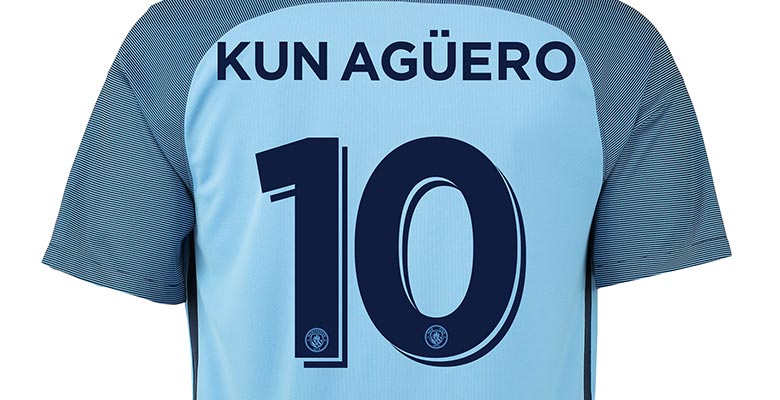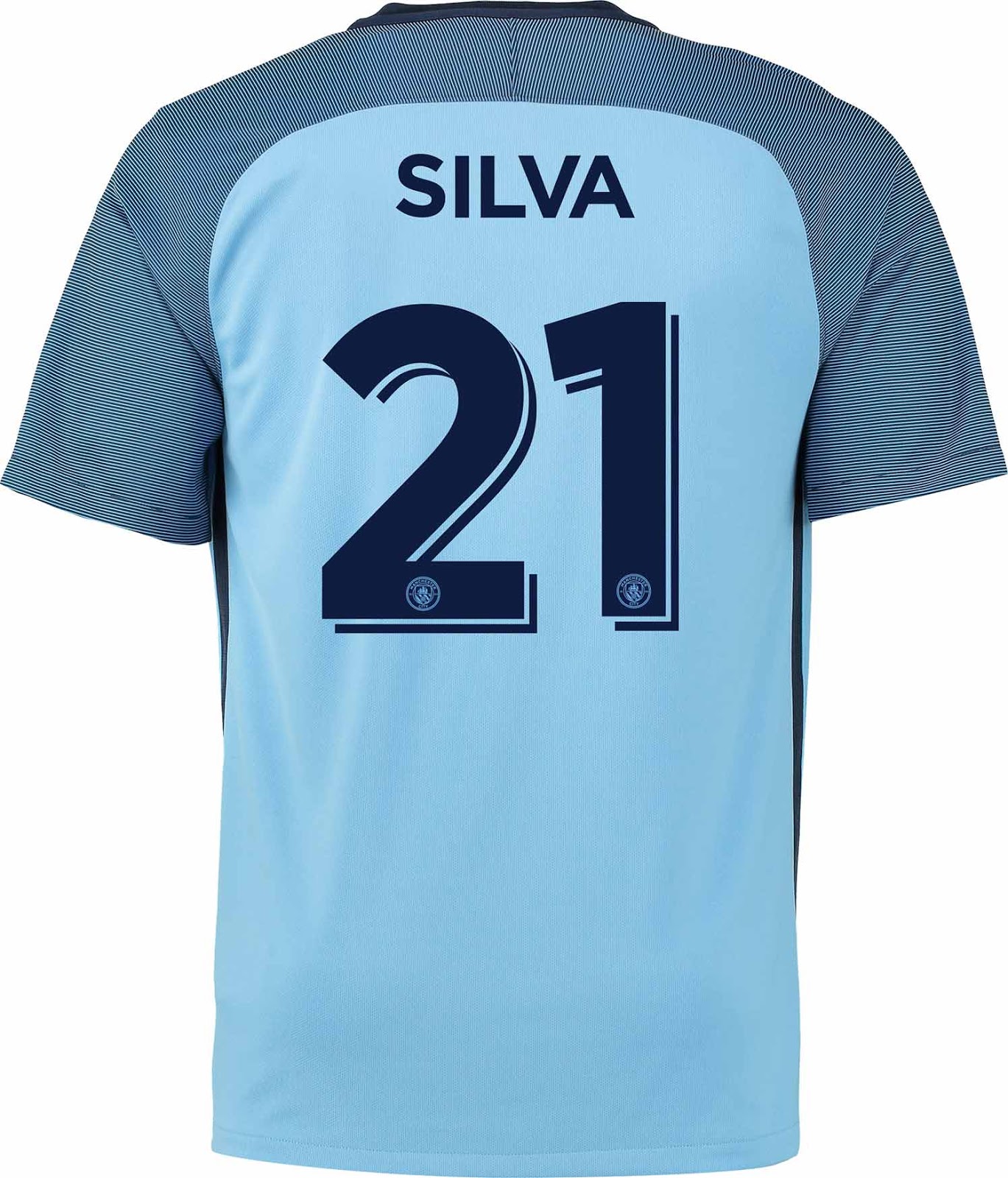
Manchester City 16-17 Schriftart enthüllt
Passend zum neuen Vereinswappen, der optischen Identität und den Trikots, hat Manchester City auch die Schriftart aktualisiert. Weil die Premier League ihre eigene ligaweite Schriftart hat, wird die neue Man-City-Schriftart nur in Pokalwettbewerben verwendet.
Manchester City 16-17 Schriftart
Das ist die neue Schriftart, die für Spielernamen und -nummern auf den neuen Manchester City 2016-2017 Trikots verwendet wird.
Die neue Schriftart, die dunkelblau auf dem himmelblauen Manchester-City-Heimtrikot und gelb-schwarz auf dem schwarzen Auswärtstrikot ist, wurde von der Schriftart inspiriert, die innerhalb des neuen Vereinswappens verwendet wird. Es ist eine gewagte und simple serifenlose Arbeit und weist das City-Wappen am unteren Ende auf. Zu guter Letzt ist ein feiner Schatteneffekt vorhanden.